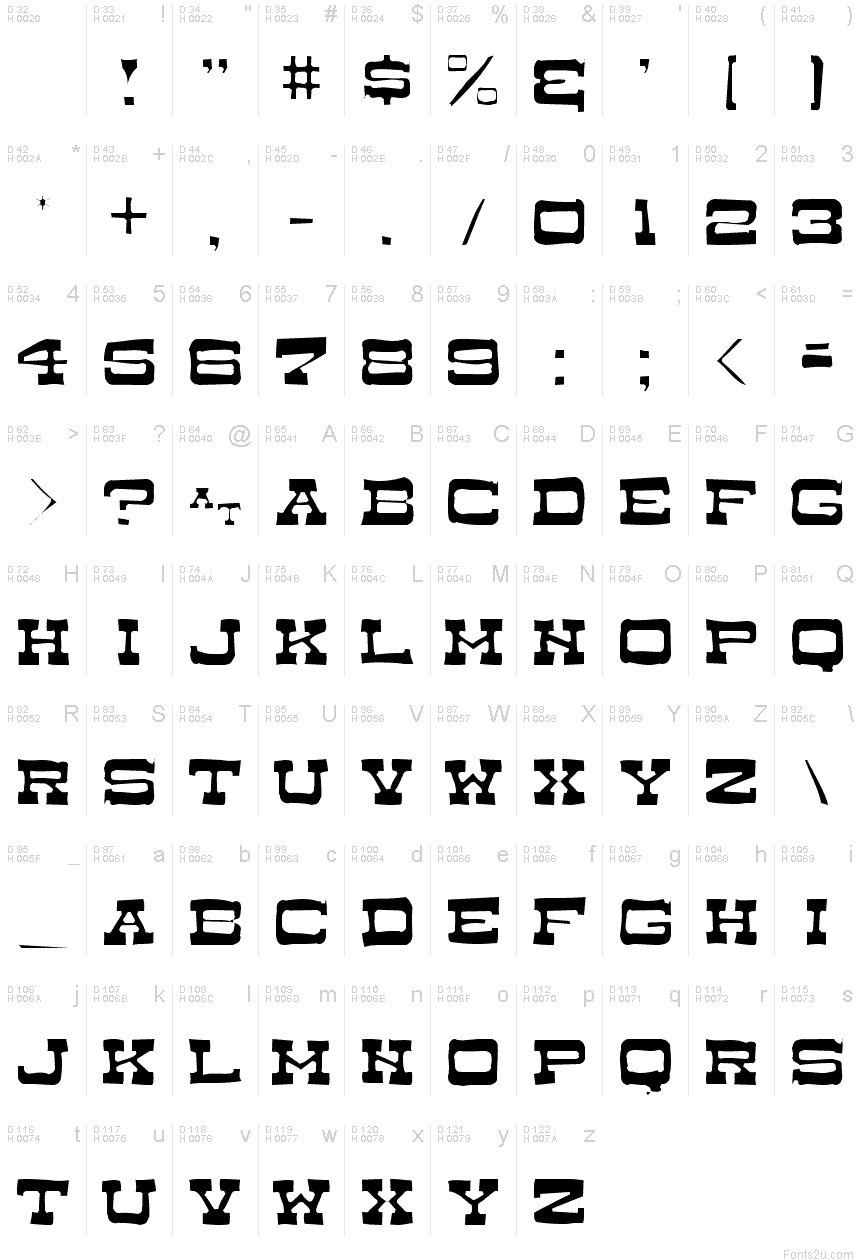
Dry Goods Antique JL de Jeffrey N. Levine es una tipografía display gratuita de estilo western que parece sacada directamente de un letrero polvoriento. Sus letras robustas y cuadradas, con bordes desgastados y sombras de tinta, le dan ese aire a sello de madera que grita «viejo Oeste». El espaciado es estrecho y contundente, haciendo que las palabras encajen como los tablones de la puerta de un salón, manteniendo su fuerza incluso en titulares de gran tamaño.
Usa Dry Goods Antique JL para crear la marca de asadores, bares estilo salón y festivales country, o para diseñar pósteres, folletos de rodeo, invitaciones a fiestas temáticas, gráficos de escape rooms y packaging vintage. Esta fuente gratuita triunfa donde necesites una tipografía potente, áspera y llena de historia que llame la atención al instante. Para lograr equilibrio, combínala con una sans serif condensada sencilla para el texto pequeño y deja que Dry Goods Antique JL se encargue de los grandes titulares.